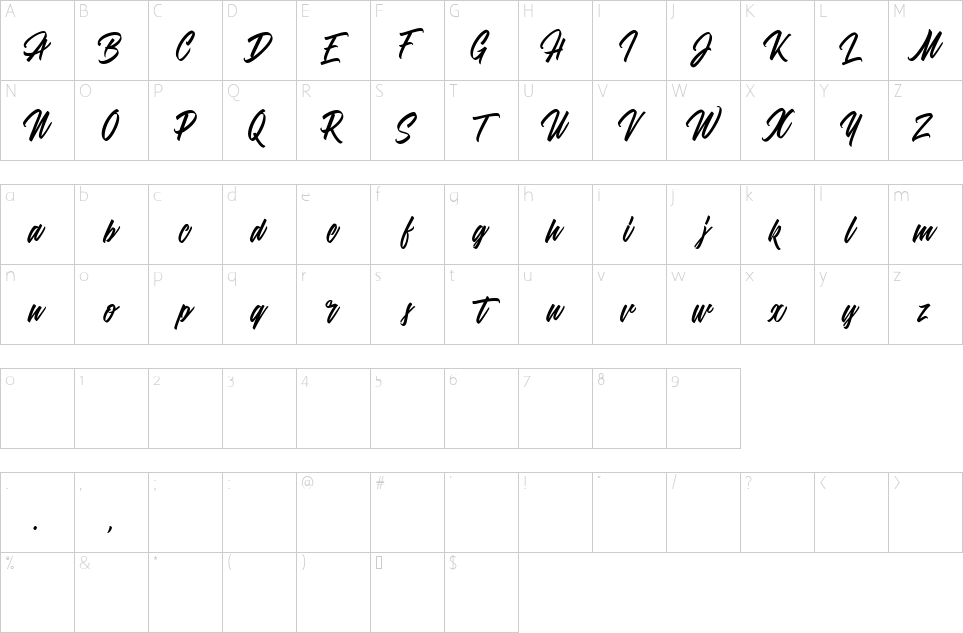
Descubra a elegância e o encanto da Jasmine Vellonica font, uma opção gratuita e versátil para personalizar textos em seu site ou aplicativo. Desenhada por Metafontsy, esta fonte vela ao pé da letra um estilo delicado e suave que combina perfeitamente com designs gráficos contemporâneos. Seja você criador de design web, designer de interfaces ou simplesmente alguém que busca adicionar uma pitada de sofisticação aos seus projetos digitais, a Jasmine Vellonica oferece as linhas finas e traços delicados necessários para dar vida a sua ideia única. Com seu estilo velloso, esta fonte é perfeita para criar um texto lúdico ou uma tipografia elegante em qualquer dispositivo: seja em um design minimalista de interface ou no layout do seu site corporativo. Com o Jasmine Vellonica Font gratuitamente disponível para download tanto em sistemas Windows quanto Mac, você pode experimentar essa fonte envolvente sem qualquer limite. Seja você criador, designer ou simplesmente alguém que aprecia uma boa fonte gráfica, esta é a escolha perfeita para trazer um toque especial ao seu projeto digital. Não perca tempo: baixe sua cópia da Jasmine Vellonica e deixe suas criações brilharem com estilo.